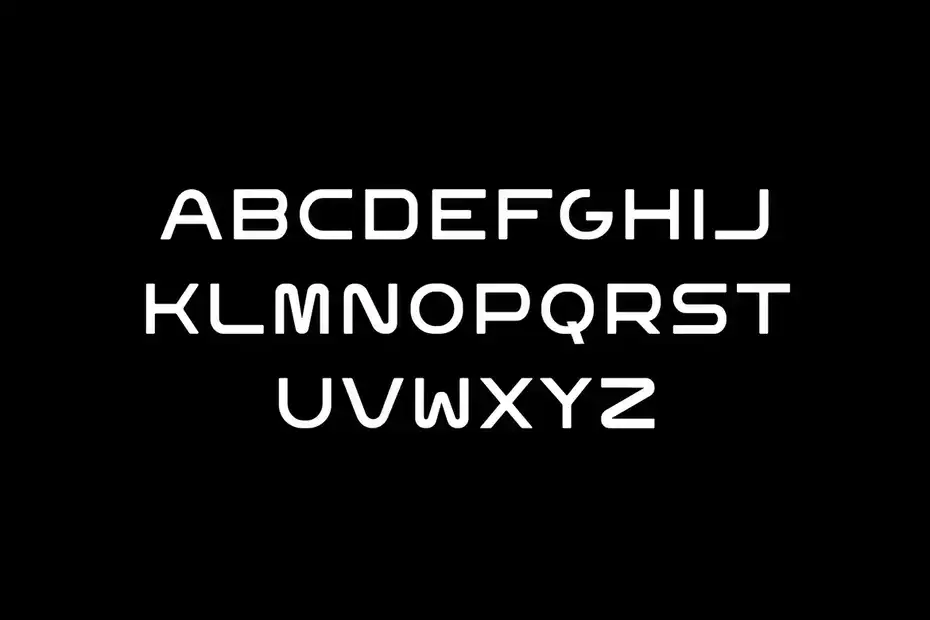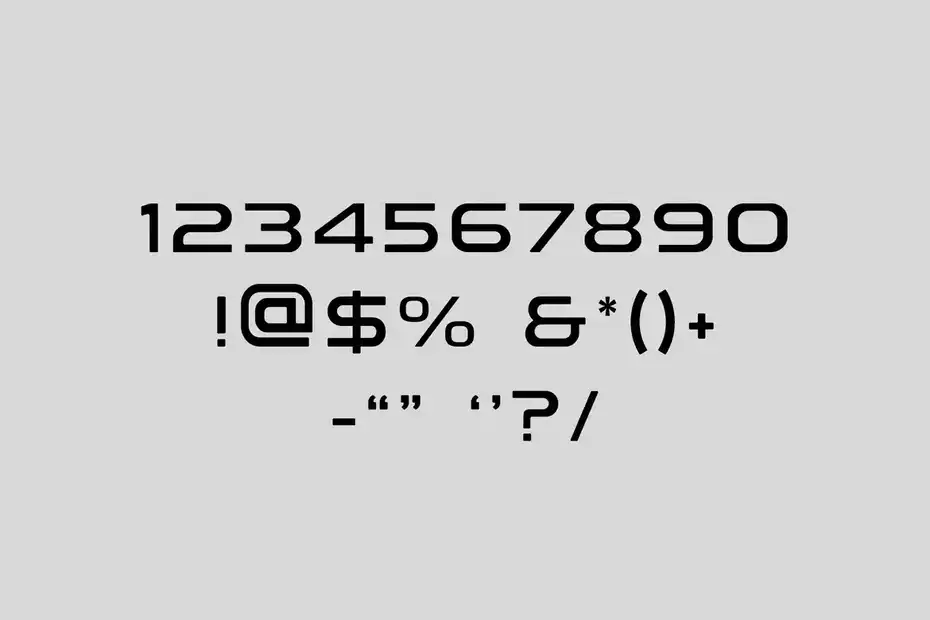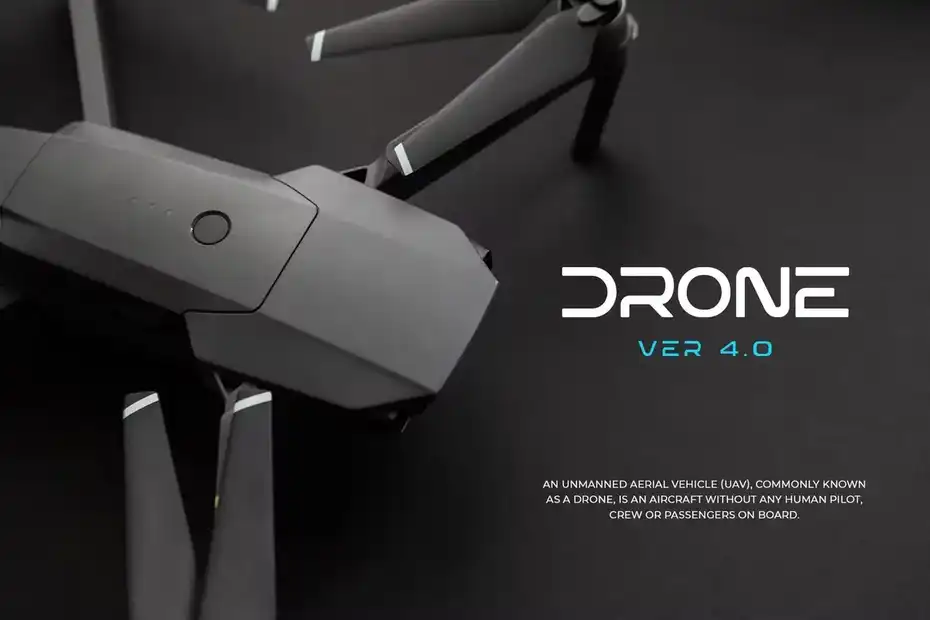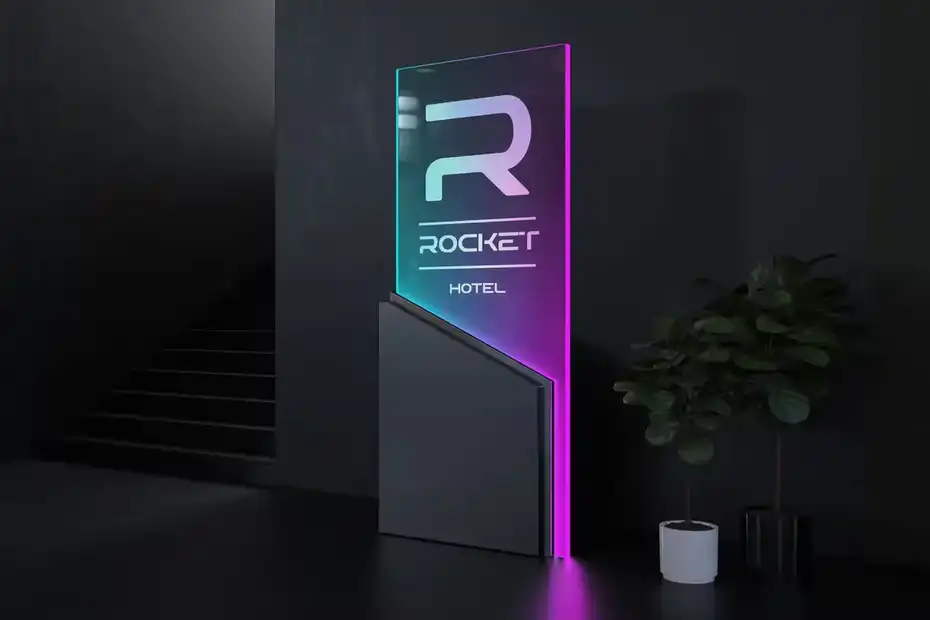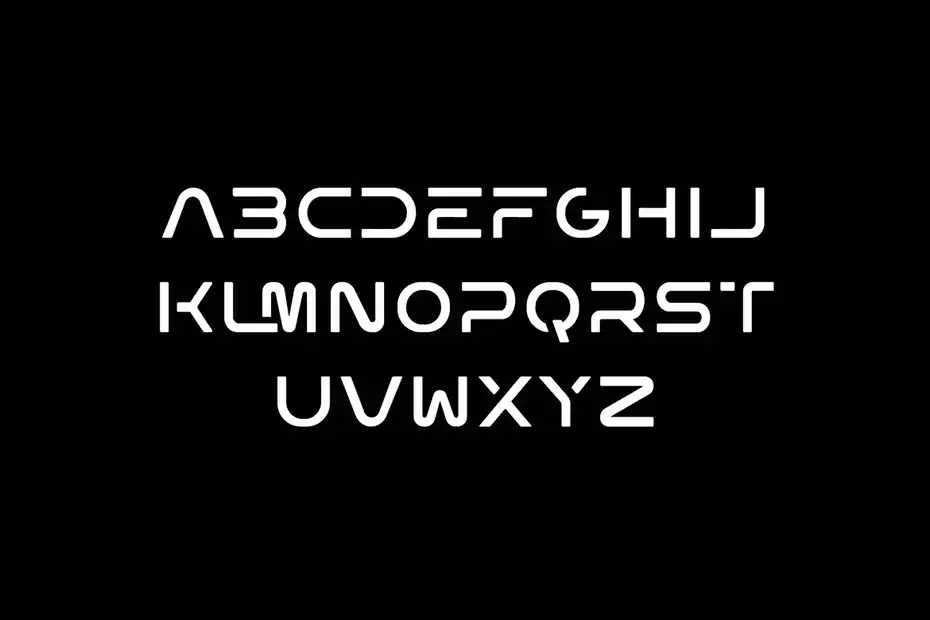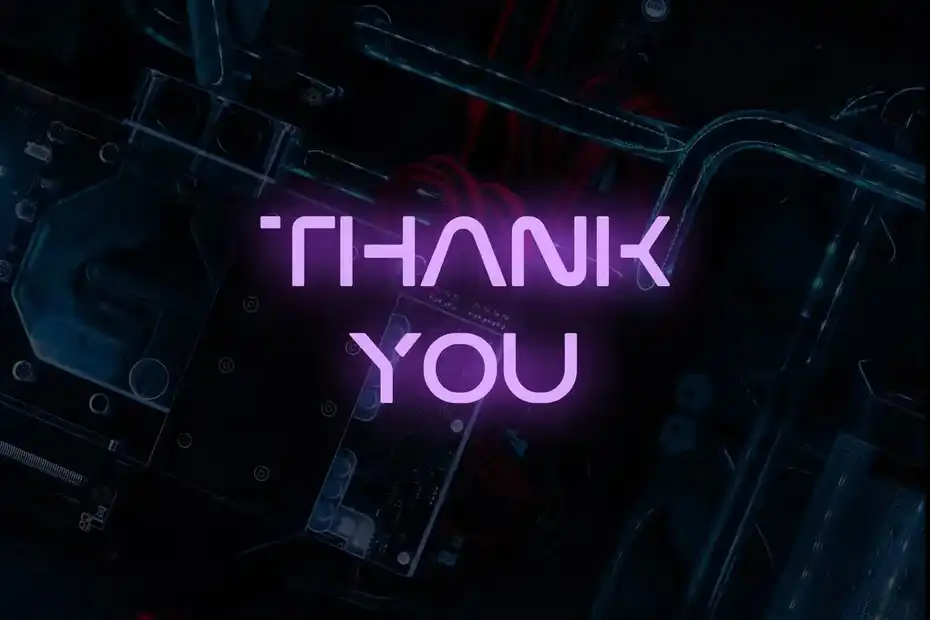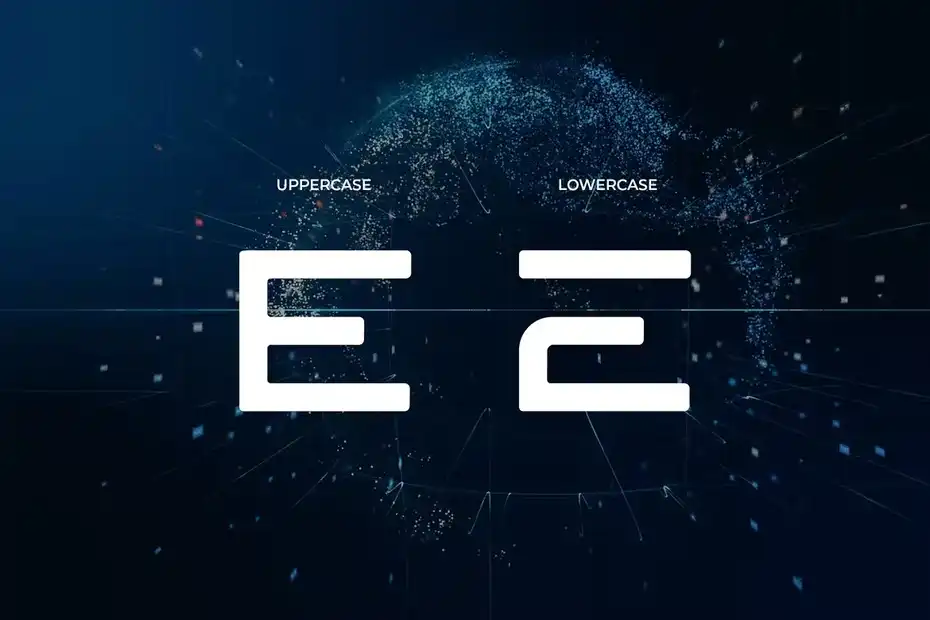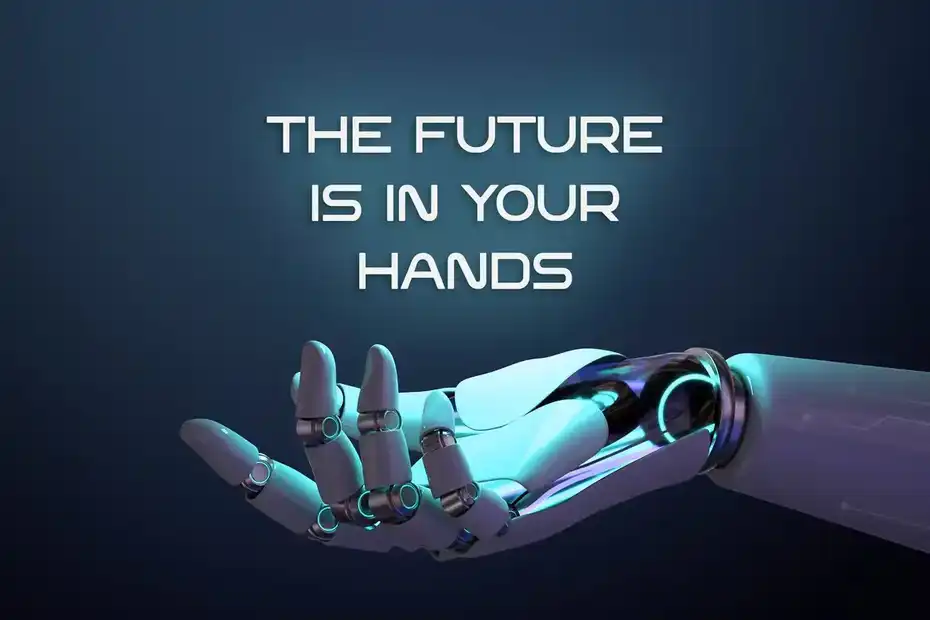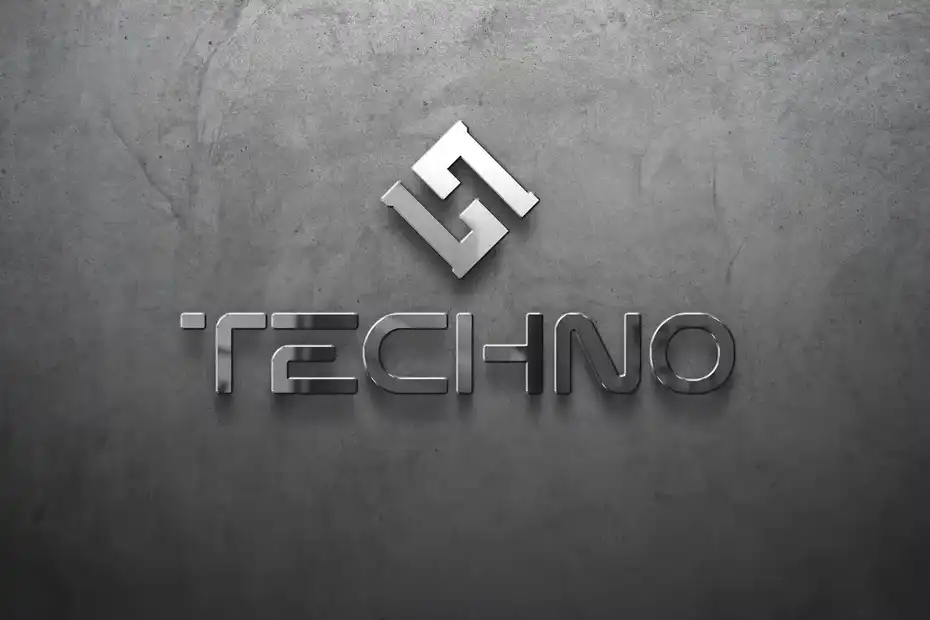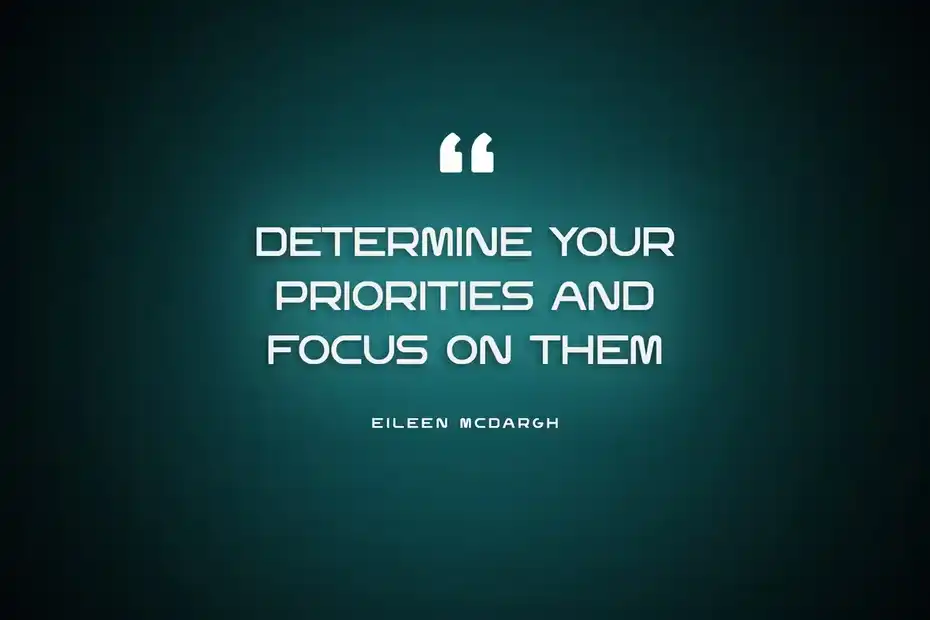
دانلود فونت انگلیسی Valko Capela Futuristic Sans Serif Font
فونت انگلیسی Valko Capela Futuristic Sans Serif Font : این مجموعه شامل یک فونت فانتزی است که برای امضا، برندینگ، لوگو، کارت، عروسی، نقل قول‌ های تایپوگرافی، کاور مجله یا کتاب، سربرگ وب‌سایت، لباس، طراحی بسته‌ بندی و غیره مناسب میباشد.